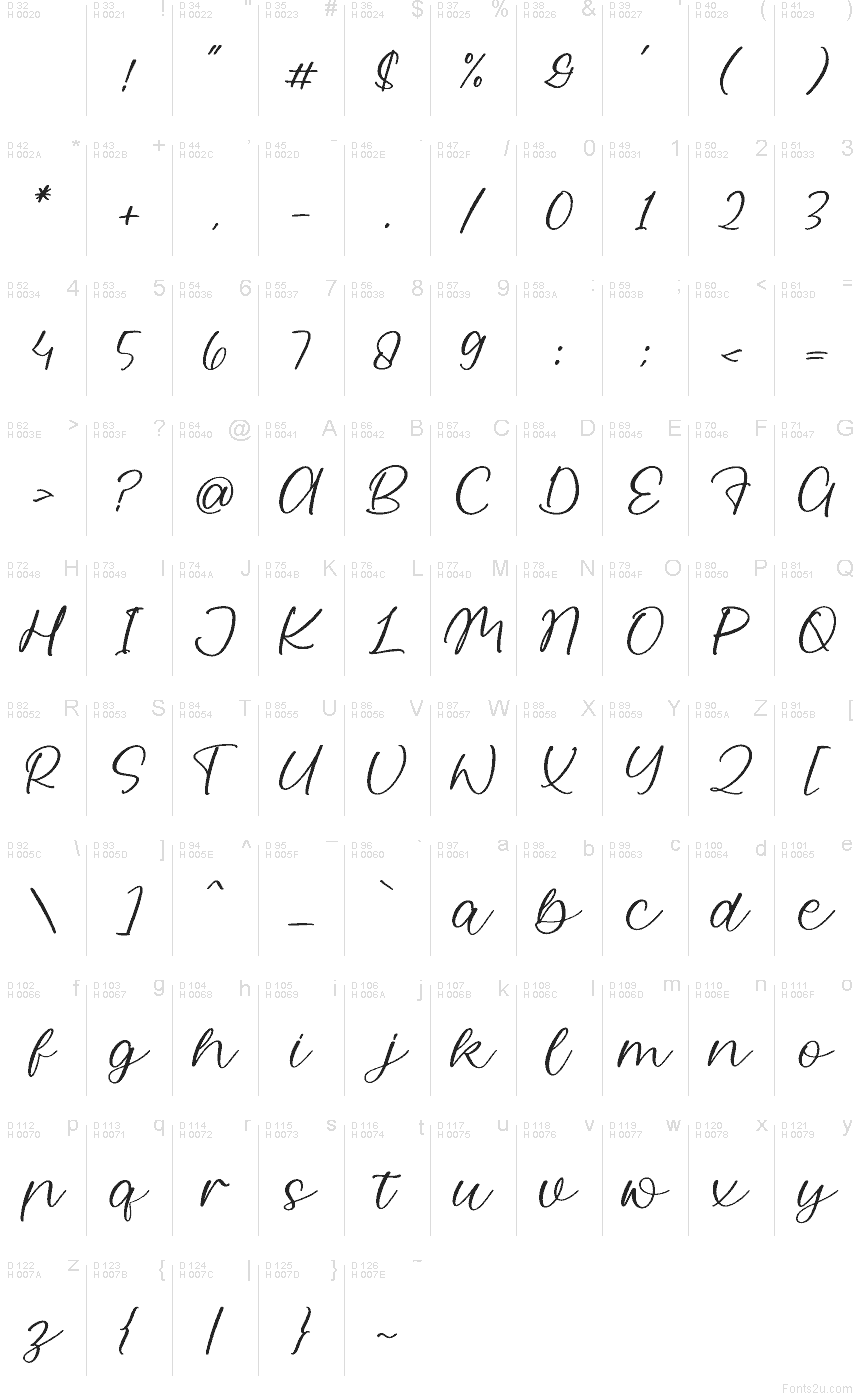
Sutllewis Flonida, da Perspectype Studio, é uma fonte caligráfica gratuita com maiúsculas altas e fluidas e um traço fino e flexível. Laçadas amplas e variações rápidas na espessura do traço dão às letras a leveza de uma assinatura, com diversos prolongamentos que vão bem além das formas principais.
Os convites de casamento são a sua aplicação mais evidente, onde os floreios generosos podem compor a maior parte da decoração. O branding de moda, as embalagens de cosméticos e a papelaria para eventos também combinam com o seu movimento, todos com a elegância de um nome desenhado à pena com confiança.